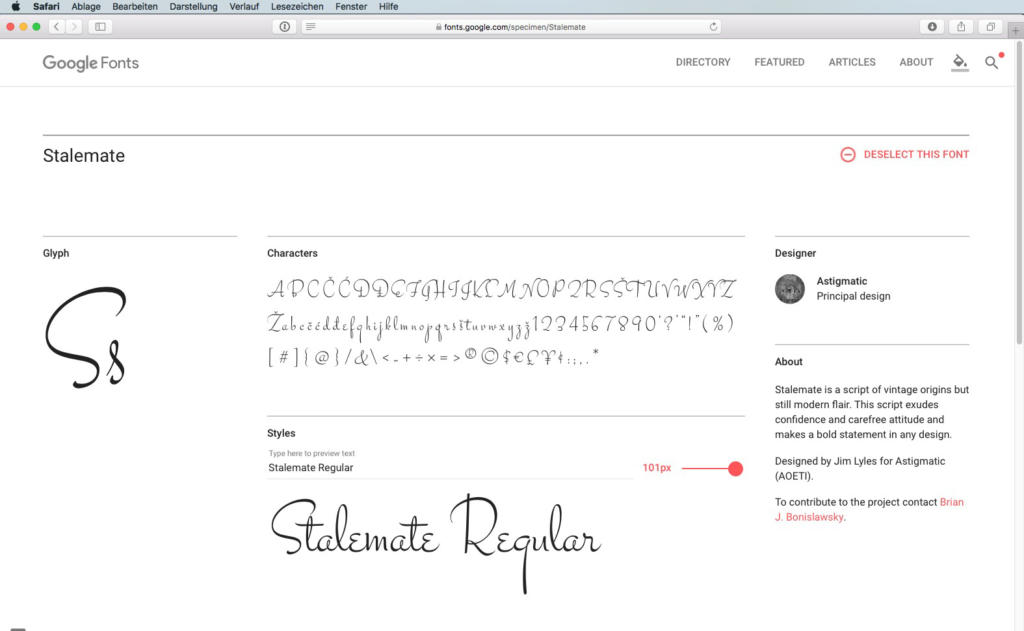
Script Fonts sind nicht erst seit gestern ein beliebtes Stilmittel in der Gestaltung. Einige der Schreibschriften sind an die Kalligraphie-Kunst angelehnt, andere an eine individuelle Handschrift. In jedem Fall weisen viele von ihnen einen unverwechselbaren Charakter auf und können deswegen einem Design eine persönliche und individuelle Note verleihen. Wir stellen Ihnen zehn angesagte Script Fonts von Google vor, die Sie kostenlos herunterladen und verwenden können.
1. Die Handschrift Delius
Die Delius von Natalia Raices ist eine an eine Handschrift angelehnte Skriptschrift. Sie steht recht aufrecht, hat ein klares Schriftbild und weist relativ große Mittellängen auf, was auch in kleinen Größen für eine gute Lesbarkeit sorgt. Übrigens hat die Delius auch eine Schwester namens Delius Swash Caps, bei der die Großbuchstabenformen verspielter sind.
Script-Font Delius Regular
2. Die klassische Fredericka the Great
Die Formen der Fredericka the Great basieren auf einer klassischen Serifenschrift; durch ihre gewollt ungenaue Linienführung und vor allem durch ihre manuell wirkende Schraffierung erhält sie ihren Sketch-Charakter. So hat Designer Tart Workshop eine interessante Mischung aus klassizistischer Eleganz und unaufgeräumter Kreativität geschaffen.
Script-Font Fredericka the Great
3. Die fette Leckerli One
Gesine Todt hat mit ihrer Leckerli One eine fette Schreibschrift kreiert, die trotz ihrer dicken Strichstärke gut lesbar ist. Sie hat einen leicht unregelmäßigen Pinselcharakter und legt viel Wert auf ihre Schleifen.
Script-Font Leckerli One
4. Die Rochester aus der Art-Deco-Zeit
Der Designer der Rochester hat sich im Zeitalter des Art Deco inspirieren lassen – herausgekommen ist eine recht aufrecht stehende Schreibschrift mit vornehmer Eleganz, die einen in eine vergangene Zeit eintauchen lässt.
Script-Font Rochester Regular
5. Die Stalemate mit Federzugcharakter
Die Stalemate von Jim Lyles ist eine Schreibschrift mit Federzugcharakter. Die Mittellängen sind im Verhältnis zu den Versalien relativ klein gehalten, was neben den teilweise sehr filigranen Linien und Schwüngen das Lesen in kleinen Schriftgraden nicht gerade einfach macht. Als Auszeichnungsschrift oder als schmückendes Element in großen Größen macht die Stalemate mit ihrem Vintage-Flair aber eine gute Figur.
Script-Font Stalemate Regular
6. Die stabile Pinselschrift Yellowtail
Die Yellowtail hat einen recht kräftigen Strich, wie es sich für eine stabile Pinselschrift gehört. Das kleine „e“ wirkt etwas fremd in der sonst harmonischen Schrift, aber wer sich damit anfreundet und nicht zu müde ist, um ab und an bestimmte Buchstabenabstände manuell auszugleichen, hat mit der Yellowtail einen guten Fang gemacht.
Script-Font Yellowtail Regular
7. Die lebendige Dancing Script
Die Dancing Script ist eine der wenigen Script Fonts, die in zwei Schnitten vorliegt, nämlich in einer normalen und einer Bold-Variante. Ihren Namen hat sie sicherlich der Tatsache zu verdanken, dass es keine einheitliche Grundlinie gibt – die Versalien ragen leicht nach unten heraus und auch die Kleinbuchstaben „tanzen“ leicht auf der Grundlinie. Zudem unterscheiden sich die Kleinbuchstaben noch leicht in den Höhen der Mittellängen – gerade genug, um ein sehr lebendiges Erscheinungsbild zu erzeugen, aber nicht so stark, als dass es für zu viel Unruhe sorgen würde.
Script-Font Dancing Script Regular
8. Die Alex Brush der 50er
Die Alex Brush ist schon eine ganze Weile recht gut im Geschäft und das nicht zu unrecht. Mit ihrem Hang zu verspielten Details hat sie besonders ansehnliche Versalformen, die aber zu jeder Zeit und auch in kleinen Größen gut lesbar sind. Sie ist eine vielseitige, schwungvolle Schrift mit einem großen Einsatzbereich.
Script-Font Alex Brush Regular
9. Leicht krakelig – die Cedarville Cursive
Die Cedarville Cursive von Kimberly Geswein ist eine eher unruhige Handschrift, die durch ihre Kanten und unrunden Schwünge leicht krakelig wirkt. Ob sie ihren individuellen Charme ausspielen kann, ist stark von den verwendeten Buchstaben abhängig. Einige Großbuchstaben fügen sich auch mit gutem Zureden nicht harmonisch in das Schriftbild ein; andere hingegen machen einen guten Eindruck und sind im laufenden Text auch gut lesbar.
Script-Font Cedarville Cursive
10. Clicker
Die Clicker hat einen eleganten Zeichenfeder-Charakter bei nur wenig wechselnder Strichstärke. Sie federt elegant und leicht auf der Schriftlinie und hat durch ihren dünnen Strich eine vornehme Zurückhaltung – eine gute Wahl für edel wirkende Gestaltungen mit individueller Note.
Script-Font Clicker Script